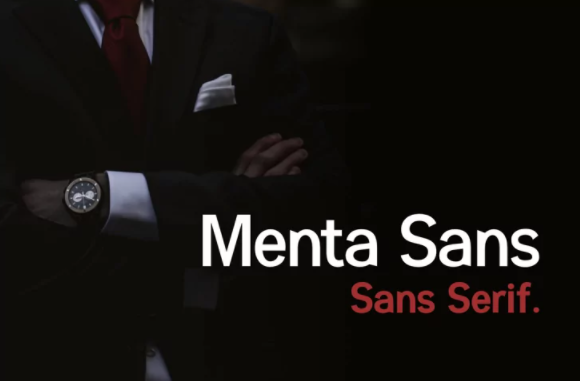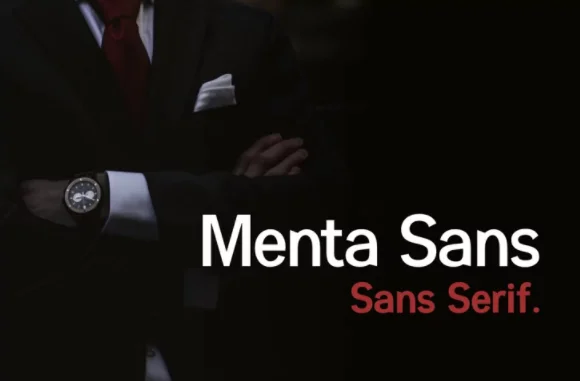
[Fontbundles] Menta Font (2021)
Название: Menta Font (2021)
Menta Sans -
элегантный шрифт Sans Serif, созданный компанией Dumadistyle. Благодаря естественному и современному стилю, этот шрифт идеально подходит для оформления ваших проектов. Menta Sans был создан, чтобы помочь вам улучшить качество вашего дизайна, особенно в брендинге вашей компании. Этот шрифт включает 6 семейств шрифтов: Regular, Italic, Thin, Thin Italic, Bold, Bold Italic, с верхним и нижним регистром.
Шрифт Menta Sans имеет современный стиль, который идеально подходит для различных целей дизайна, таких как логотипы, заголовки, обложки книг, брендинг, цитаты, реклама, обложка фильма, название компании, заголовок и многое другое. Посмотрите превью выше, чтобы подобрать подходящий вариант для вашего проекта. Оставайтесь стильными!